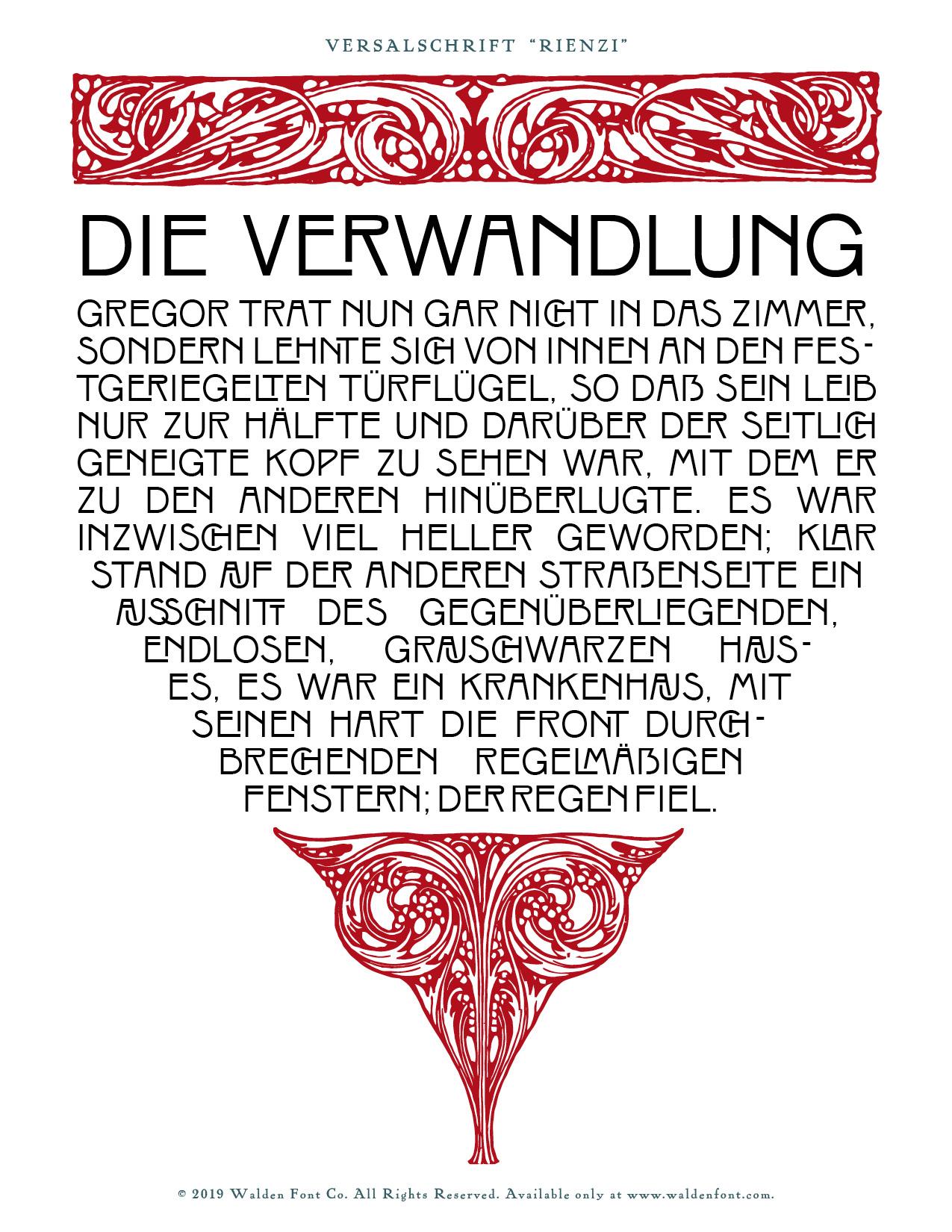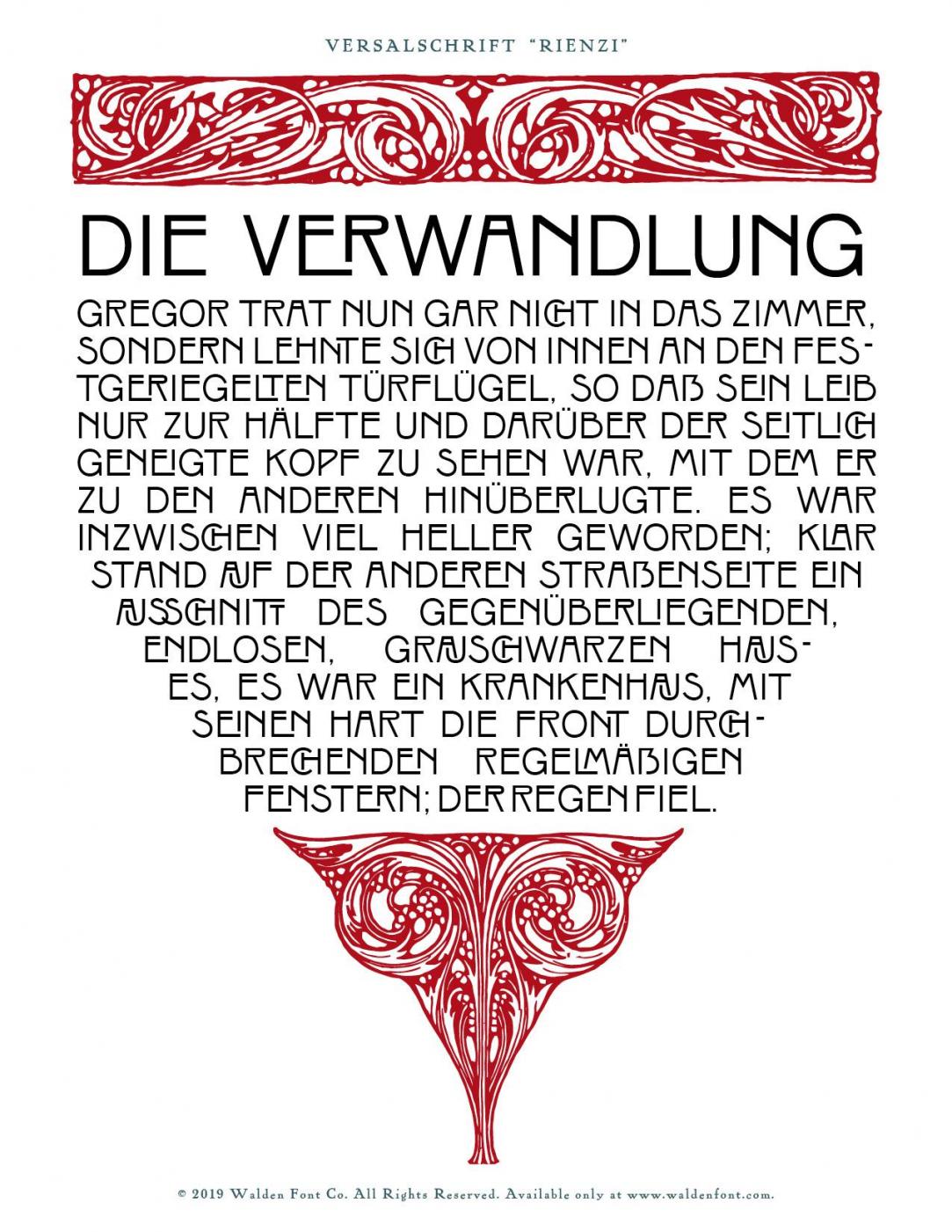
Mein Versuch zur Versalschrift "Rienzi"
Meine zweite Jugendstilschrift is soweit fertig, es ist die "Versalschrift Rienzi", wieder von Schelter & Giesecke. Ich bitte um Kritik.
Das Zeichnen war kein Vergnügen, denn bei so einer eckigen Schrift tauchen mehr optische Täuschungen auf als die Polizei erlaubt. Zudem sehen die Ziffern, die ich mir allesamt aus dem A*sch gezogen habe,  mehr nach Art Deco aus. Aber ich brauche einen Kontrast zu den anderen, blumigen Schriften, die noch kommen sollen. Vielleicht mache ich aber noch eine abgerundete Variante, mal sehen.
Was es mir bei der Rienzi besonders angetan hat, waren die Ligaturen. Einige waren in der Probe vorgegeben, darunter AU, CH und CK.  Ich habe dann gleich noch einen ganzen Haufen dazu gemacht. Wenn schon, denn schon 🙂
Worauf ich wohl eher verzichtet hätte, wäre die AJ-Ligatur aks AU und vielleicht besser keine SS-Ligaturen über Wortfugen hinweg, das ist aber jetzt nicht eine Frage der Schriftart, die mir persönlich schon gut gefällt, sondern des Muster-Satzes, wo ja auch FES-TGERIEGELT so auch nicht geht.
Vielleicht eine AU-Ligatur besser nicht ineinander verschachteln? Ich habe da mal schnel selber gezeichnet:1550837161_AuAjax.JPG.a2a3550bf4bf605b0a9db743ba2dbd3e.JPG
Vielen Dank für den Vorschlag! Da hast Du ganz recht - die AU Ligatur sieht aus wie AJ. Fast noch mehr stört mich, daß sie so dunkel ist. Warum habe ich es so gemacht? Weil sie eben so im Original vorhanden war:-? Leider vergesse ich zu oft einen Ratschlag, den Matthew Carter mir gegeben hat: "Revival isn't taxidermy" - man sollte verbessern, wo man kann, und meistens kann man.
Ich mache mich also noch mal an das AU ran. Deine Version gefällt mir sehr gut, nur liest mein - primär auf Englisch funktionierendes - Gehirn das als "FU", und das heißt ja ganz was anderes...
Edit: Die rechte Version ist schick, aber vielleicht noch zu dunkel. Ich probiere sie mal etwas verbreitert.
Zur Worttrennung und so: soweit ich weiß kann mein InDesign nur Englisch. Vielleicht gibt's da eine Spracheinstellung, ich guck mal.